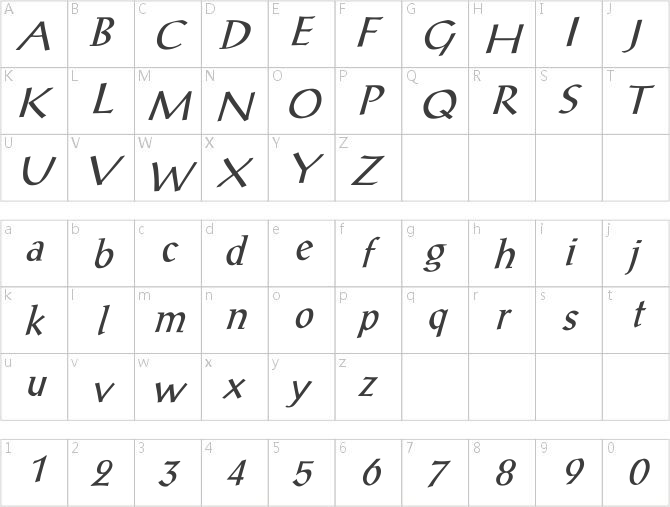
PostAntiqua-Roman-Italic
PostAntiqua-Roman-Italic介紹
PostAntiqua-Roman-Italic字體字庫是一款讓人賞心悅目、百看不厭的英文字體,適合各類廣告和產品包裝設計應用,字體大小0.1MB,格式為ttf字體,上傳用戶是123123aaa,作者/版權方為未知